このシリーズでは、書体づくりの視覚調整について紹介します。
今回は「田」を例に紹介します。
書体づくりの大まかなルールとして、「下側を広く」「右側を広く」なるように調整します。これは、人の目には下部より上部の方が、右より左の方が膨張して見える錯視を考慮しています。
シンプルな構造の「田」で説明します。
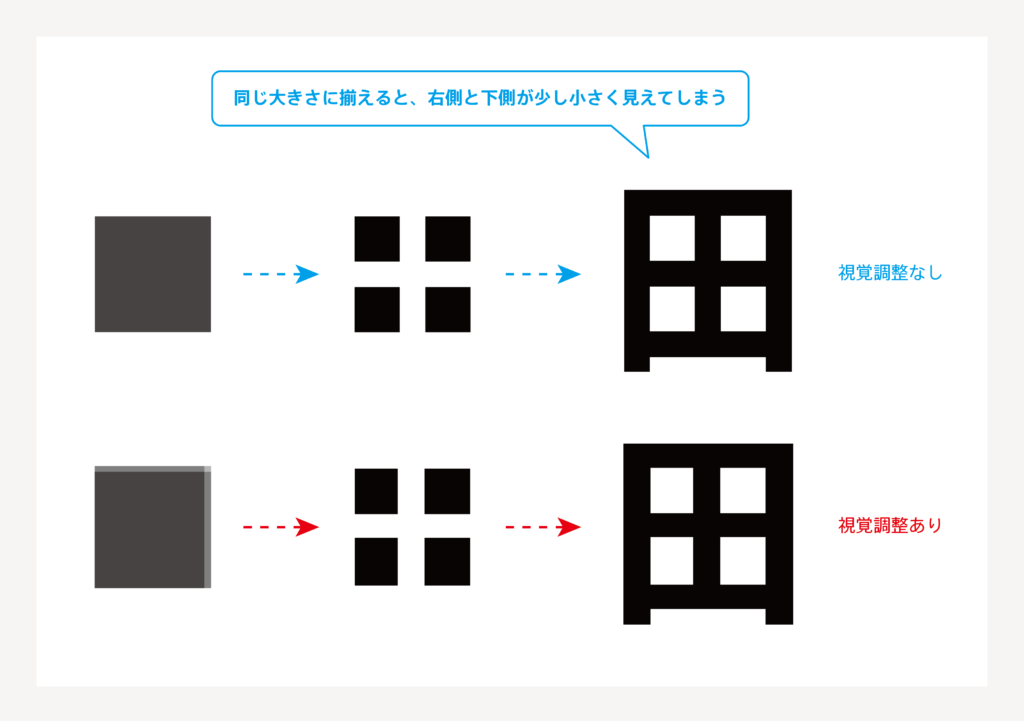
「田」という漢字は左右対象な形をしていますが、見た時に同じ大きさに見えるように、下側と右側をわざと大きく制作しています。空き部分を完全に同じ大きさで制作してしまうと、少し右側と下側が狭く見えてしまうためです。
この調整の有無は文字サイズの1%程度の違いですが、このようなわずかな差で、文字を見た時の印象は変わります。
書体づくりには、他にも線の太さや長さなどの視覚調整ポイントがあります。本シリーズの連載で、それら視覚調整のポイントを紹介していければと思います。